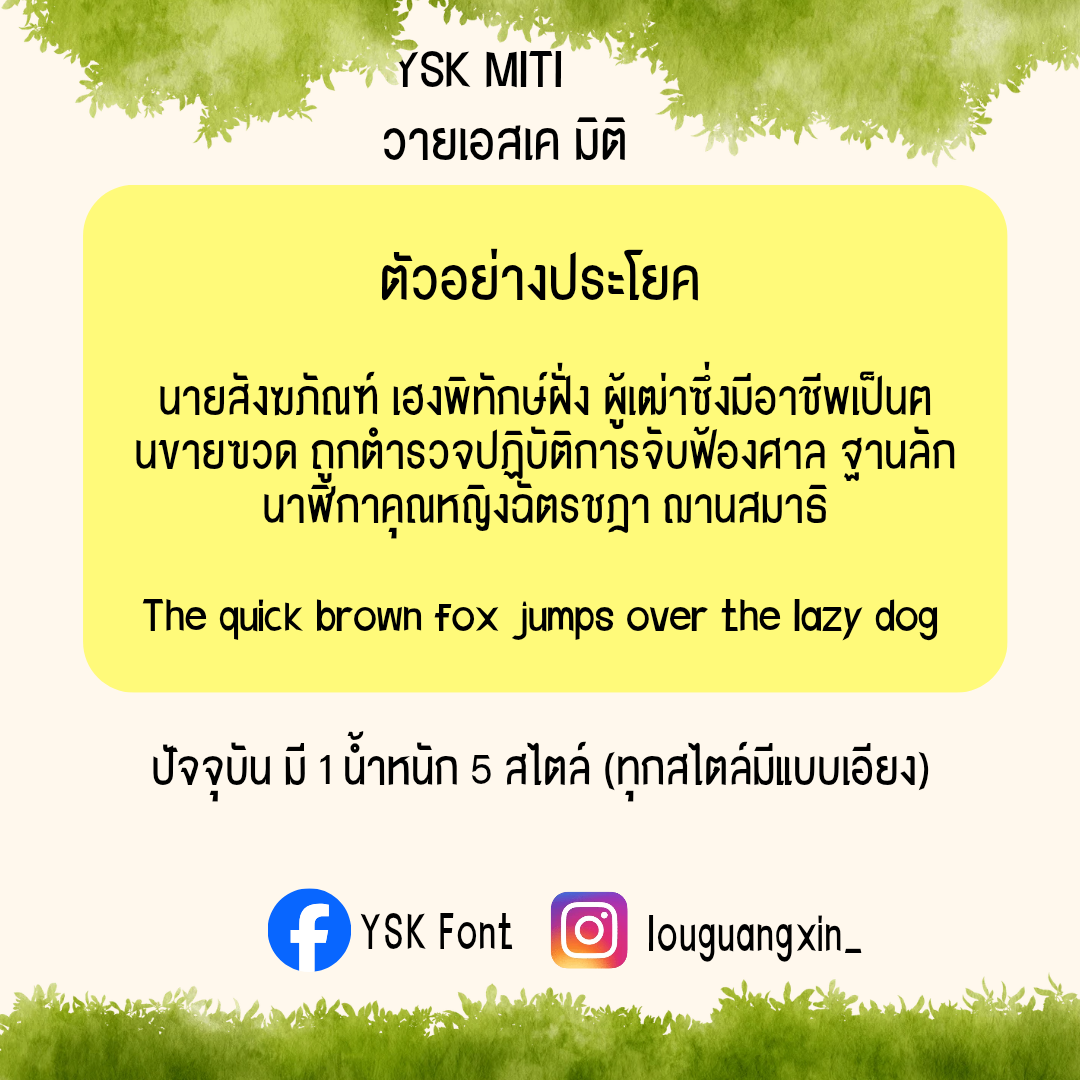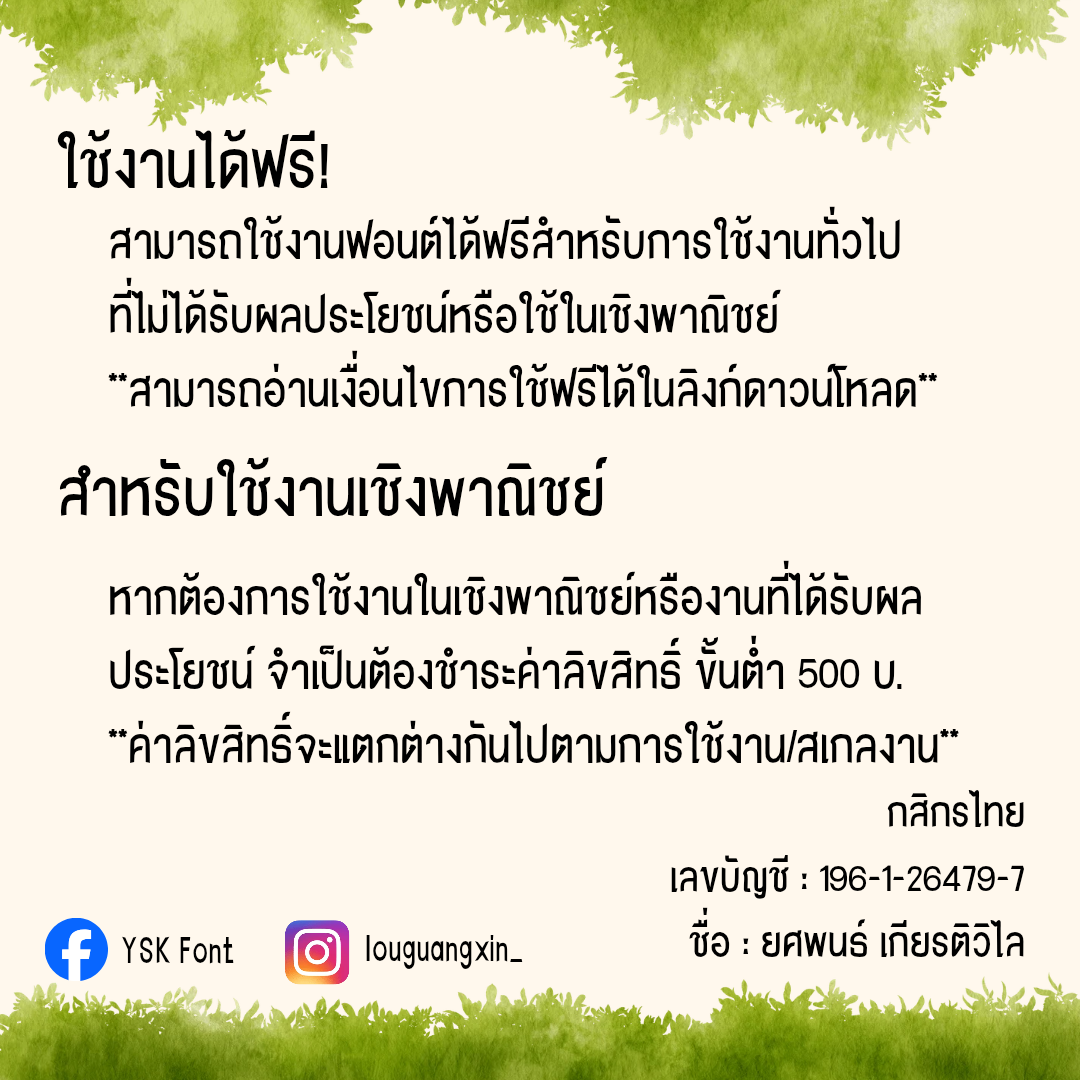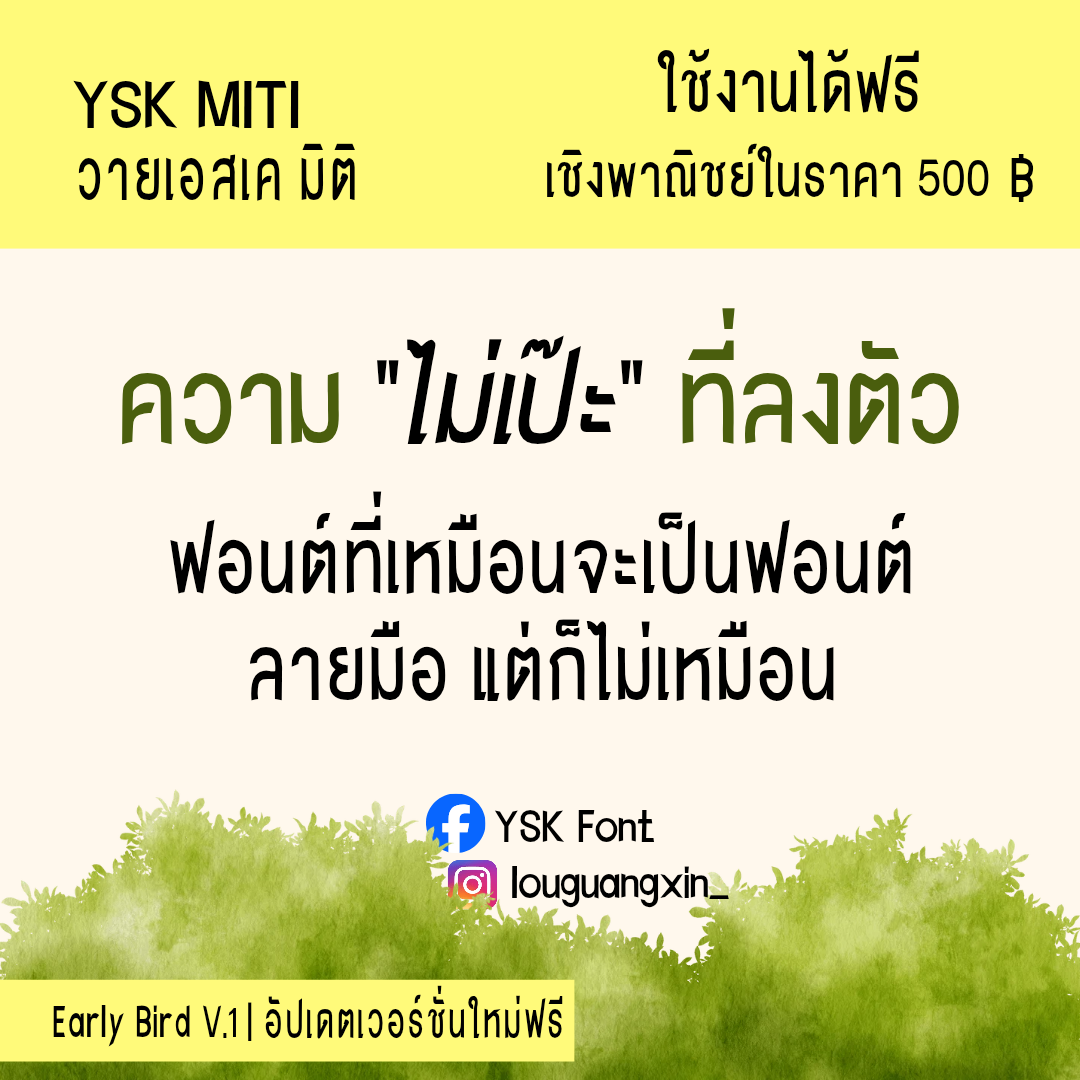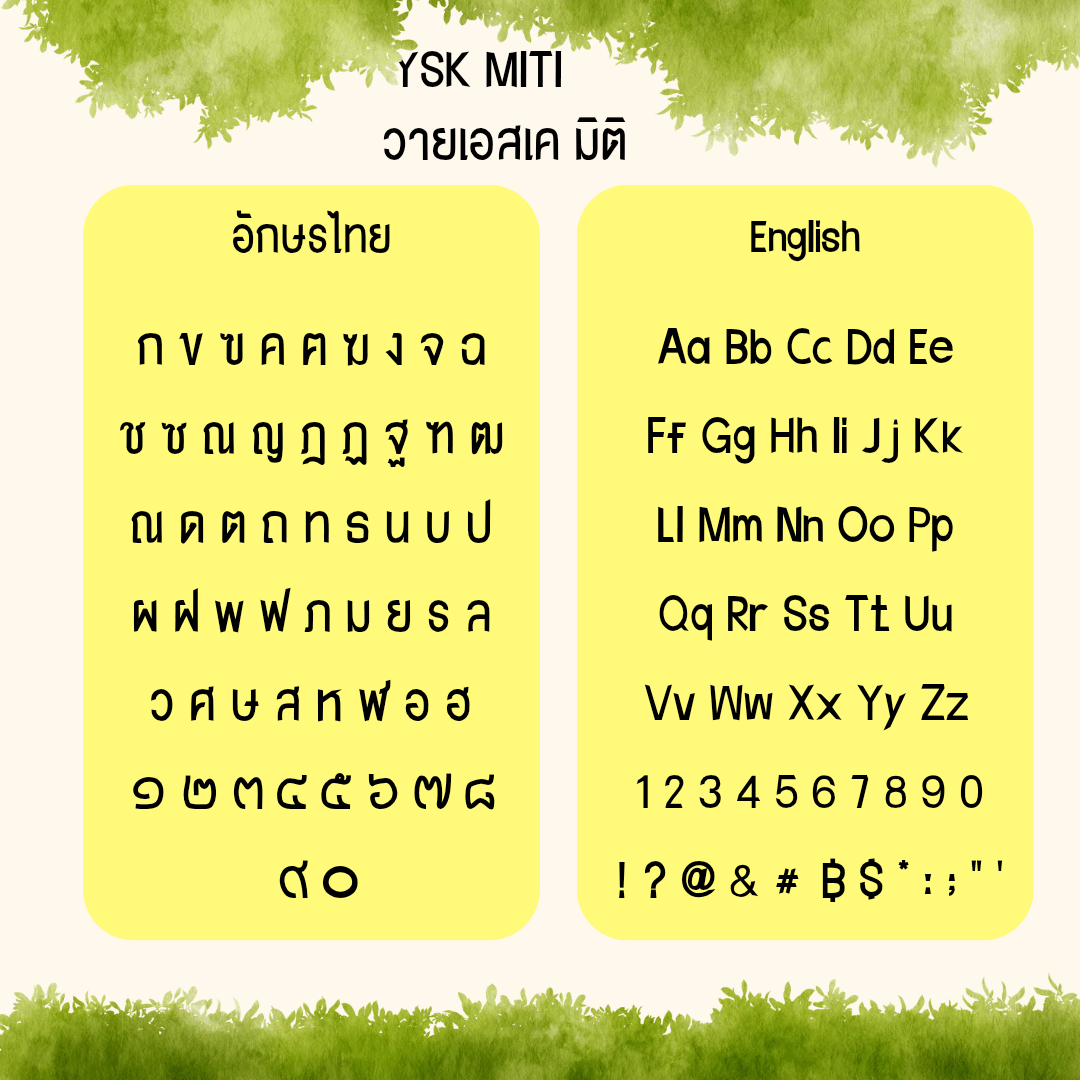
ฟอนต์ YSK MITI (วายเอสเค มิติ)
ความ"ไม่เป๊ะ"ที่ลงตัว ฟอนต์ที่เหมือนจะเป็นฟอนต์ลายมือ แต่ก็ไม่เหมือน
ปัจจุบันมี 1 น้ำหนัก 5 สไตล์ (ทุกสไตล์มีแบบเอียง)
ผู้สร้างสรรค์ : นายยศพนธ์ เกียรติวิไล